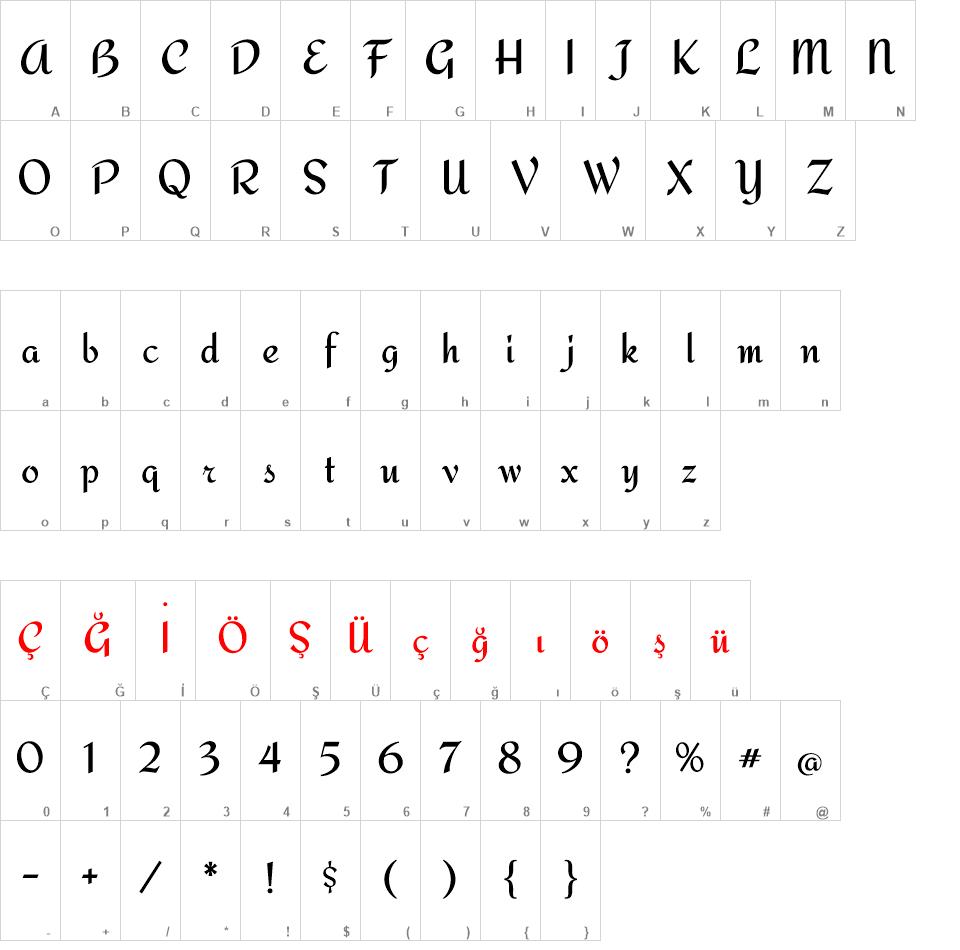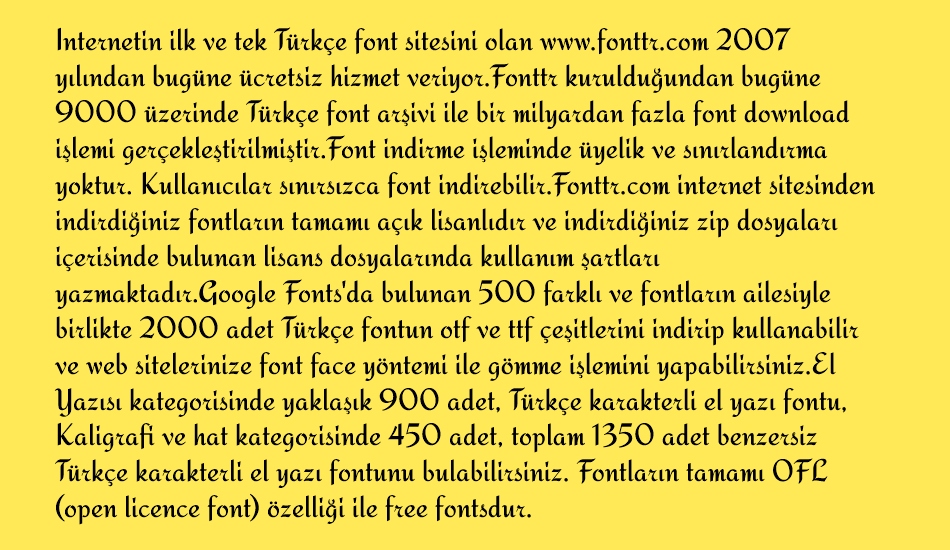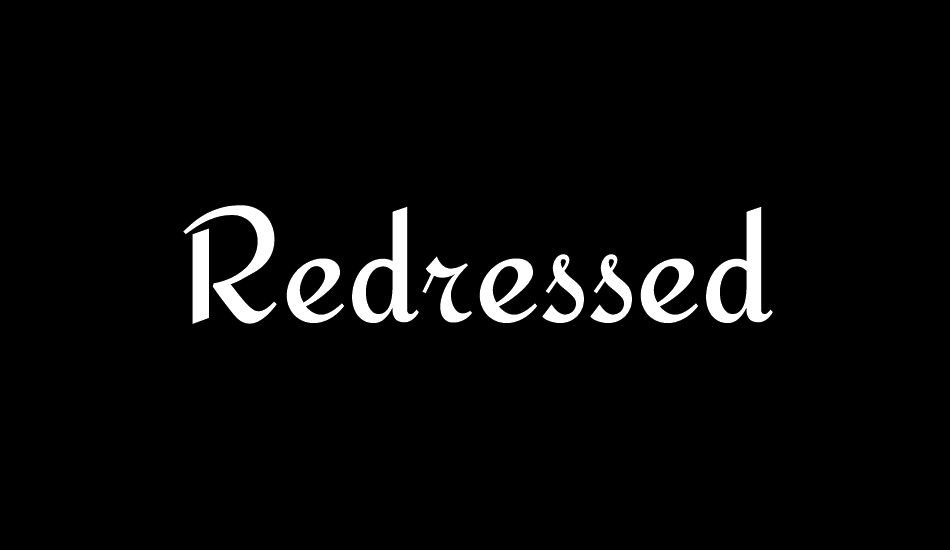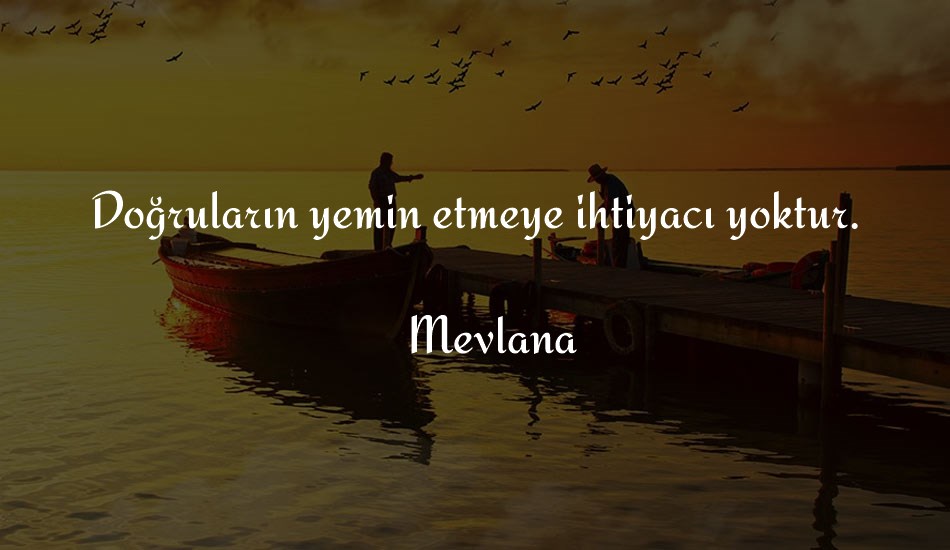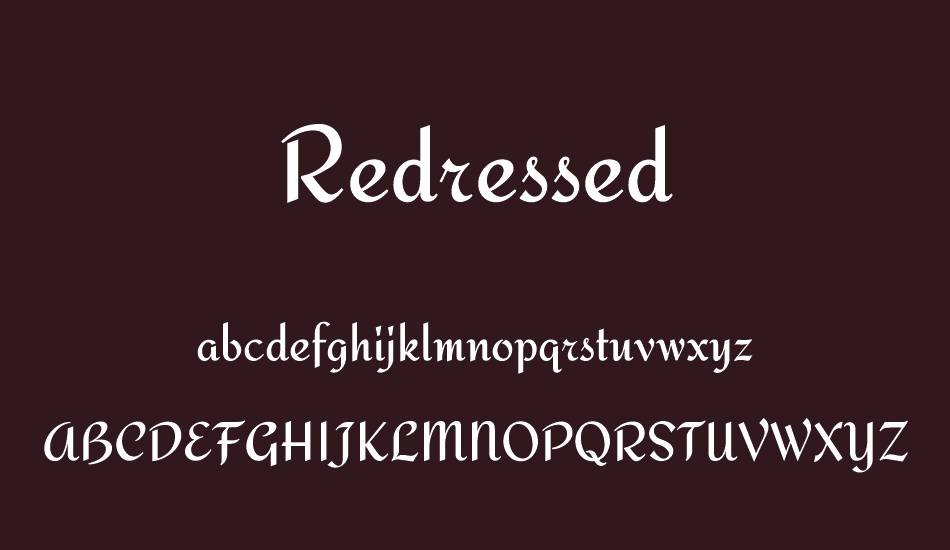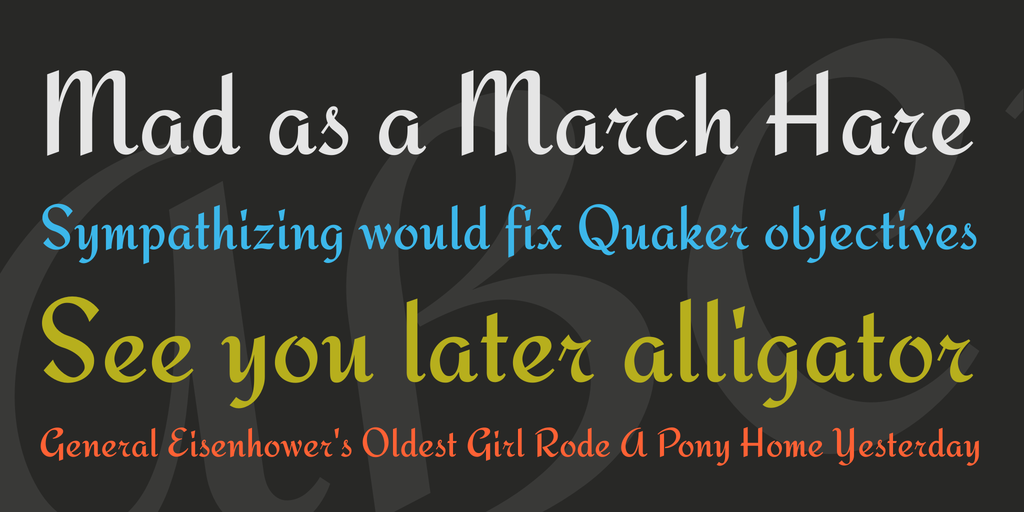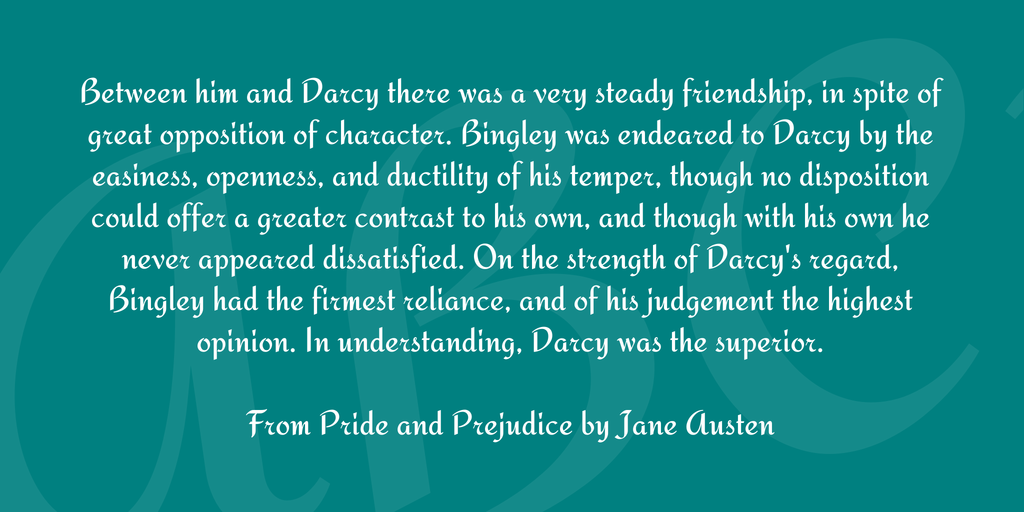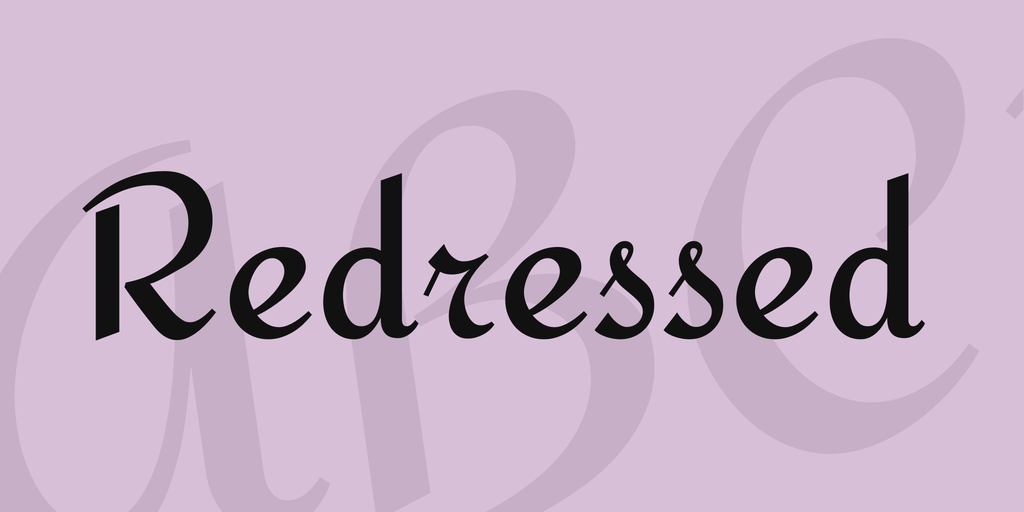
Redressed font
Redressed, betik ve italik harf biçimlerini birbirine dik olmayan bağlantı stiliyle harmanlayan orta ağırlıklı bir yazı karakteridir. Açık aralıklı ve şık harf formları, kendilerini başlık olarak kullanmalarını sağlarken, aynı zamanda vücut kopyası olarak daha küçük boyutlarda okunaklılığı temizlemektedir.